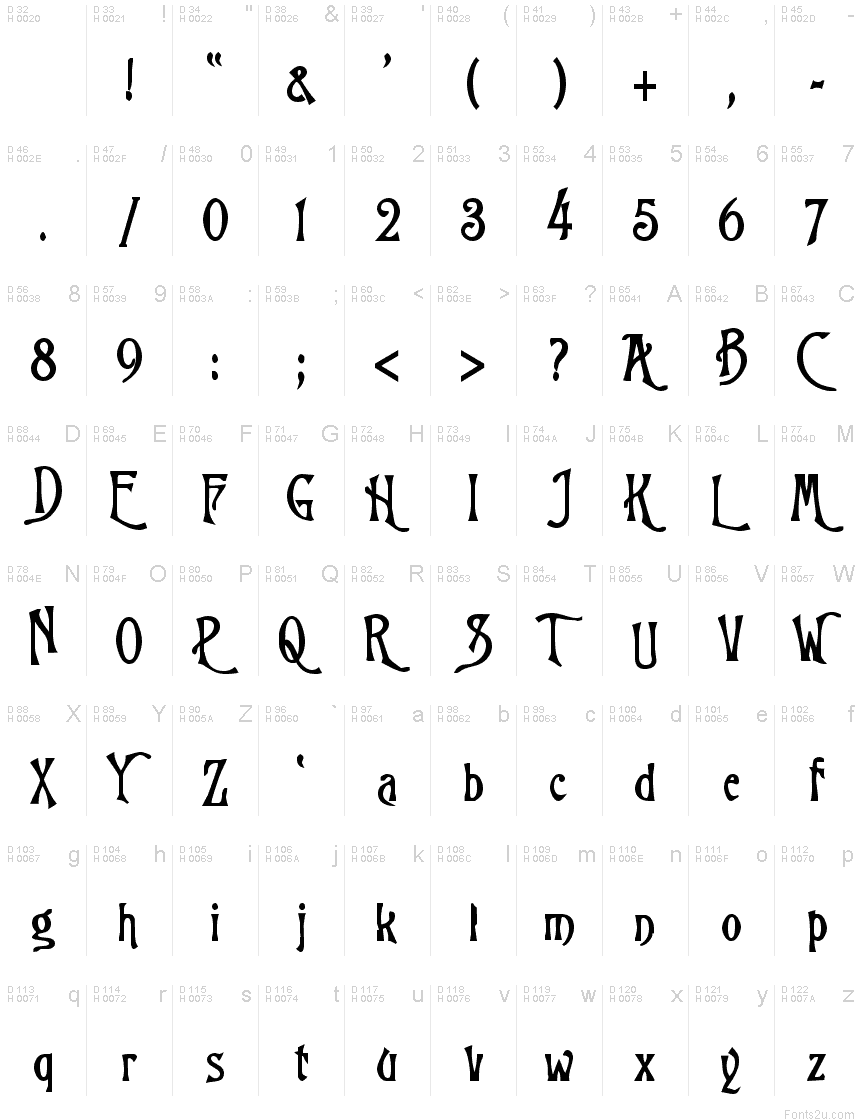
Wizard Bold od SWFTE International to darmowy, dekoracyjny krój pisma fantasy w baśniowo-średniowiecznym klimacie. Litery łączą wysokie, wąskie formy z rozszerzanymi pociągnięciami i ostro zakończonymi końcówkami, nadając fontowi charakter magicznej księgi — teatralny, a jednocześnie wyważony.
Naturalnie sprawdza się w tytułach na plakatach, logotypach gier, okładkach książek, opakowaniach tematycznych i grafikach eventowych, wszędzie tam, gdzie darmowy krój potrzebuje odrobiny folkloru i dramatyzmu. Ostro zakończone znaki i nieregularny, ręcznie rysowany rytm świetnie sprawdzają się też w krótkich nagłówkach i na planszach tytułowych, zwłaszcza gdy zależy Ci na tym, by tekst był nieco magiczny, a nie tylko historyczny.